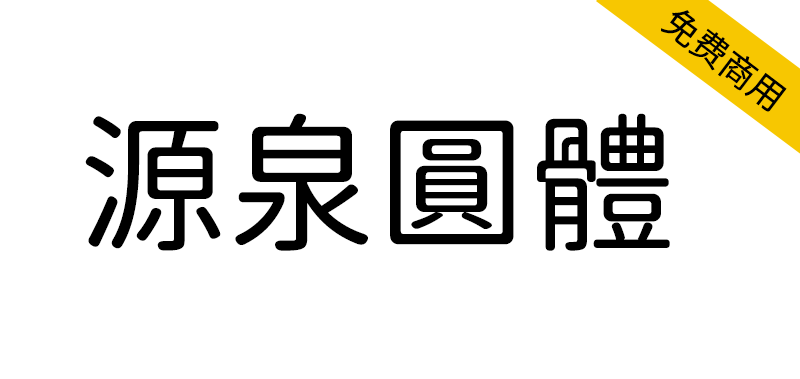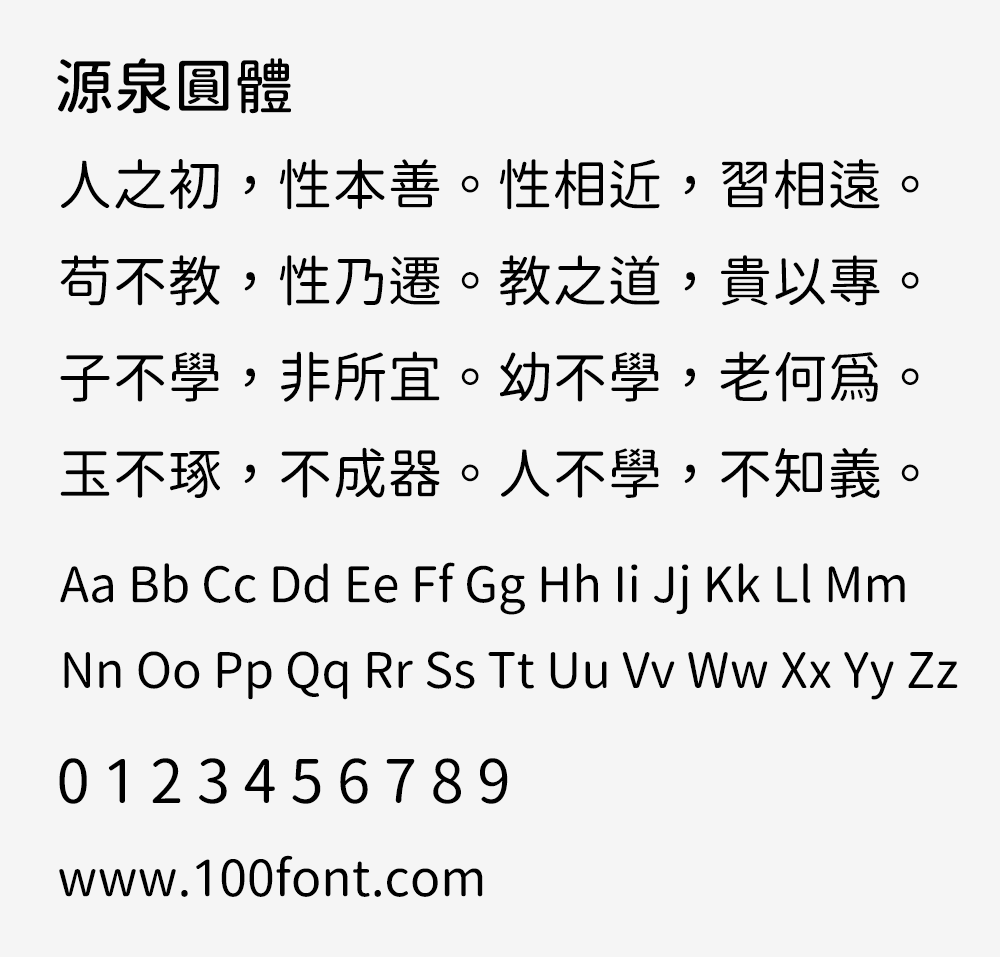
源泉圆体是基于思源黑体的开放原始码中文字体,弥补一直没有正统圆体开源字体的缺憾。黑体的开源字体非常多,但一直缺乏正统圆体的开源字体。像源柔ゴシック之类的字体都留有黑体的脚,乍看的感觉还是很黑体。
本字体不只把笔画全改圆,也将黑体的脚尽可能拔除,并加上封闭区域的内圆角处理,尽可能去逼近圆体样貌。
免责事项:本字体乃以计算机程序自动进行改造,如上述拔脚的作业充满猜测性。部分文字可能有脚没拔掉,部分文字可能正常的笔画被误判是脚而误拔。由于此为兴趣性的开源字体项目,虽已试图强化猜测算法减少误判,但仍无法保证没有错误。在正式场合使用时请自行确认文字正确性。基本上较细的字重效果会较好且较正确,而愈粗的字重错误会较多。